Wort eintippen, Stil wählen, PNG herunterladen. Mehr ist es nicht, und es dauert etwa zehn Sekunden.
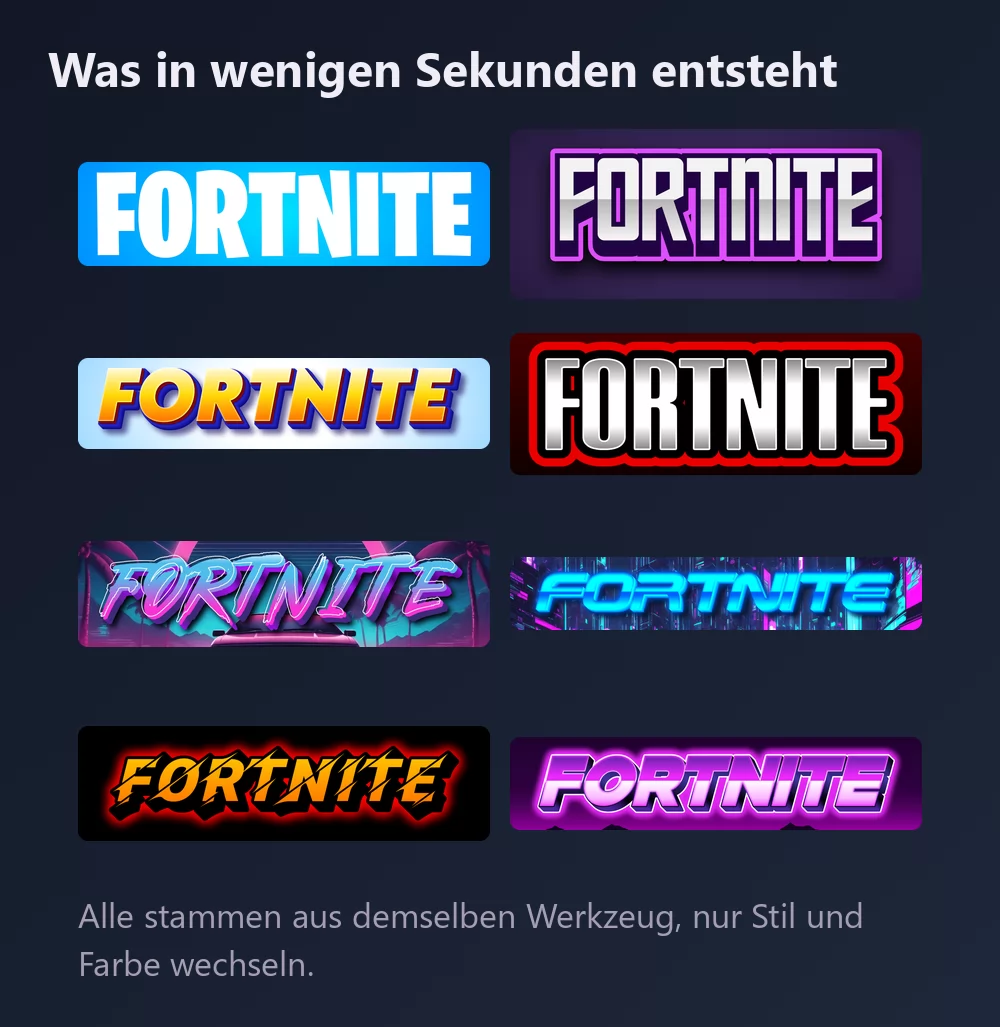
Alle stammen aus demselben Fortnite-Schriftgenerator, nur mit einem anderen Stil aus der Liste. Nichts zu installieren, kein Konto.
Über die Fortnite-Schrift
Fortnite ist ein Sandbox-Survivalspiel von Epic Games und People Can Fly. Es erschien am 25. Juli 2017 im kostenpflichtigen Early Access, und erst der später hinzugekommene kostenlose Battle-Royale-Modus machte daraus ein Phänomen.
Die Schrift im Logo ist Burbank Big Condensed von Tal Leming, in abgewandelter Form verwendet. Burbank ist eine Displayfamilie, gebaut für genau solche Aufgaben, und umfasst rund zwanzig Schnitte. Burbank Big gibt es in drei Breiten mit je vier Gewichten, und die Begleiterin Burbank Small ist für kleine Größen gezeichnet, in vier Breiten mit je einer Kursiven.
Fortnite-Text erstellen
Schritt 1. Das Wort eintippen
Öffne den Generator und ersetze den Beispieltext durch deinen eigenen: einen Namen, ein Squad-Kürzel, einen Kanalnamen, einen Videotitel. Die Buchstaben werden beim Tippen neu gezeichnet.
Schritt 2. Einen Stil wählen
Der Klassiker sind fette weiße schmale Versalien auf einem blauen Verlauf. Im Reiter Stile lassen sich Füllung, Kontur und Schatten getrennt ändern: Die Buchstabenformen bleiben, die Farben wandern woandershin.
Schritt 3. Das Format wählen
Stell das Format vor dem Export ein, dann wird später nichts beschnitten. 16:9 für ein Video-Vorschaubild, ein Quadrat für ein Profilbild oder ein Icon, ein breiter Streifen für eine Kanal-Kopfzeile.
Schritt 4. Herunterladen
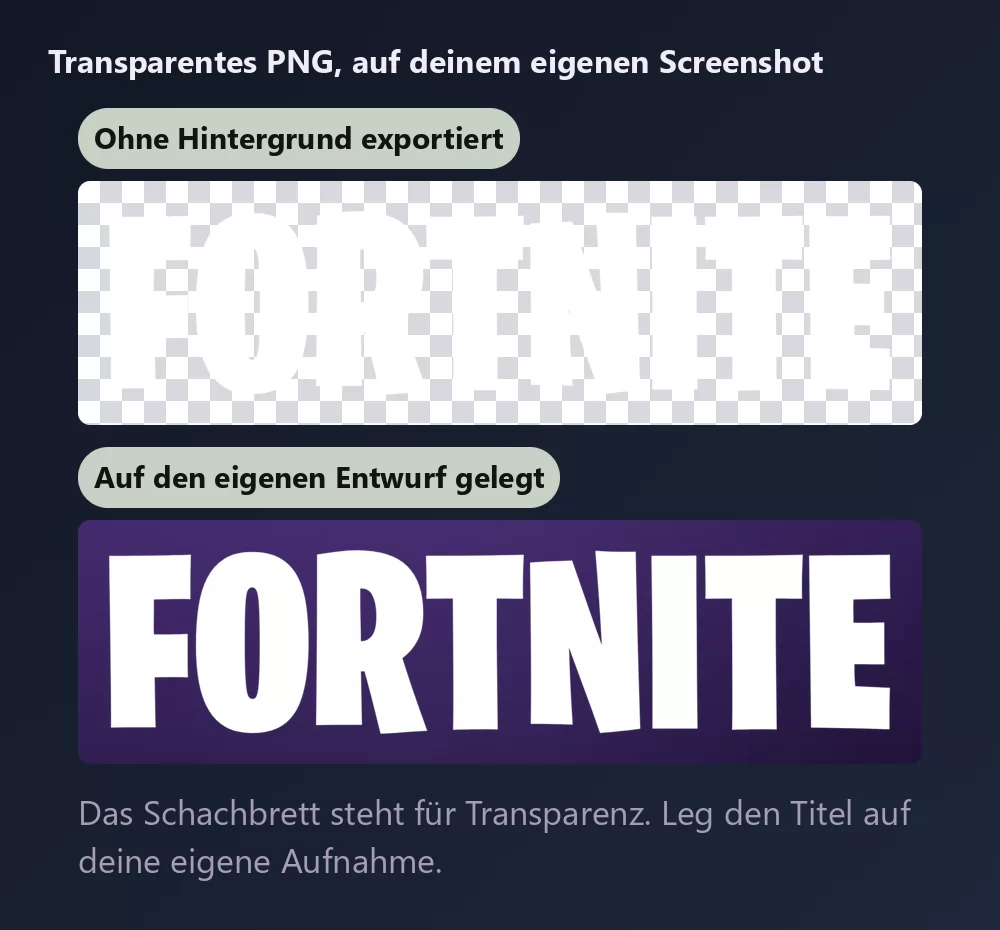
Nimm im Reiter Herunterladen das transparente PNG, wenn der Titel auf deinen eigenen Screenshot soll. Diese Option übersehen die meisten, und für ein Vorschaubild ist sie die entscheidende: deine Aufnahme dahinter, der Titel darüber, kein weißer Kasten drumherum.
Lange Namen füllen die Breite schnell
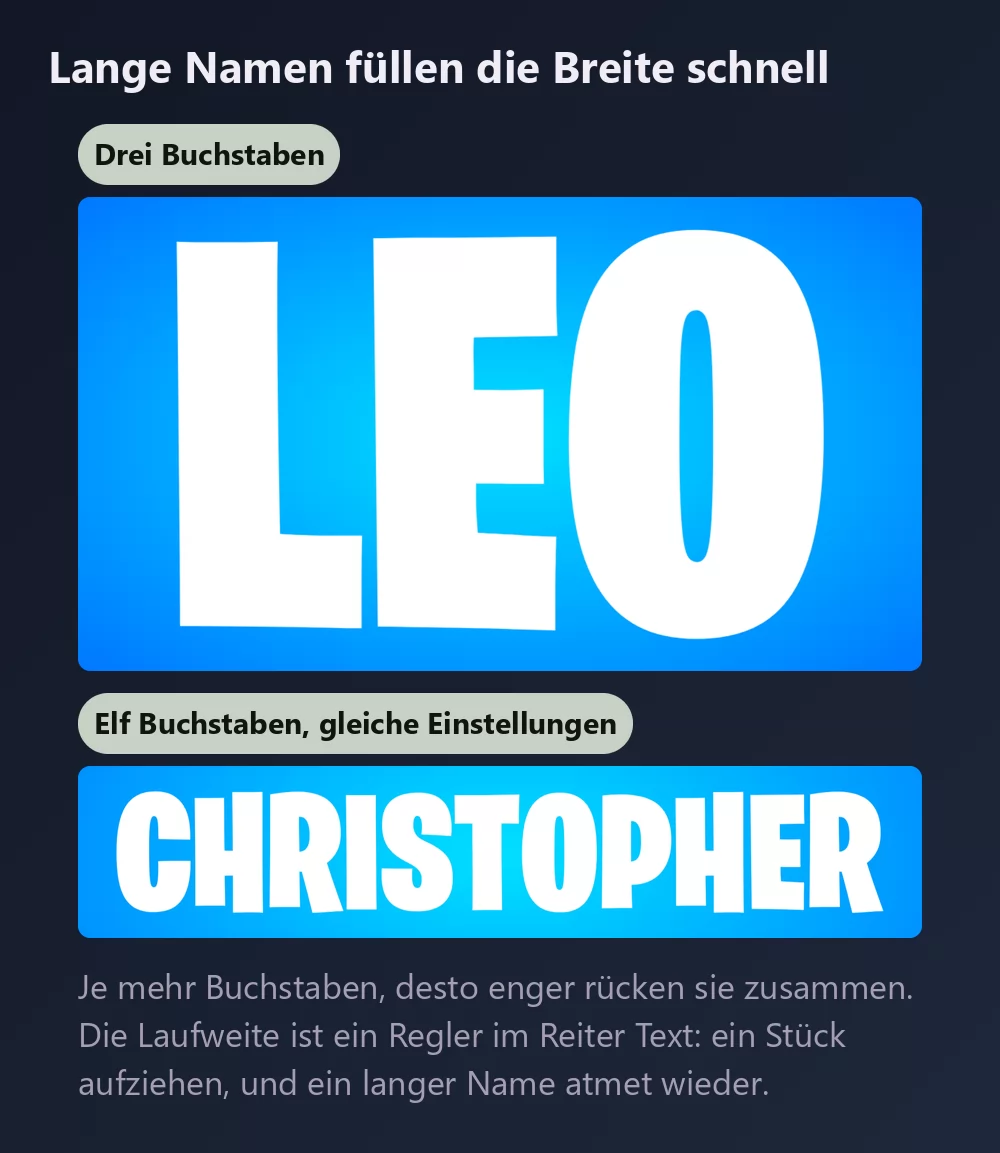
Je mehr Buchstaben, desto enger rücken sie zusammen. Die Laufweite ist ein Regler im Reiter Text: ein Stück aufziehen, und ein langer Name wirkt nicht mehr gequetscht. Im selben Reiter stecken Zoom, Zeilenabstand, Wölbung und Drehung.
Der Logo-Look oder der Esports-Look
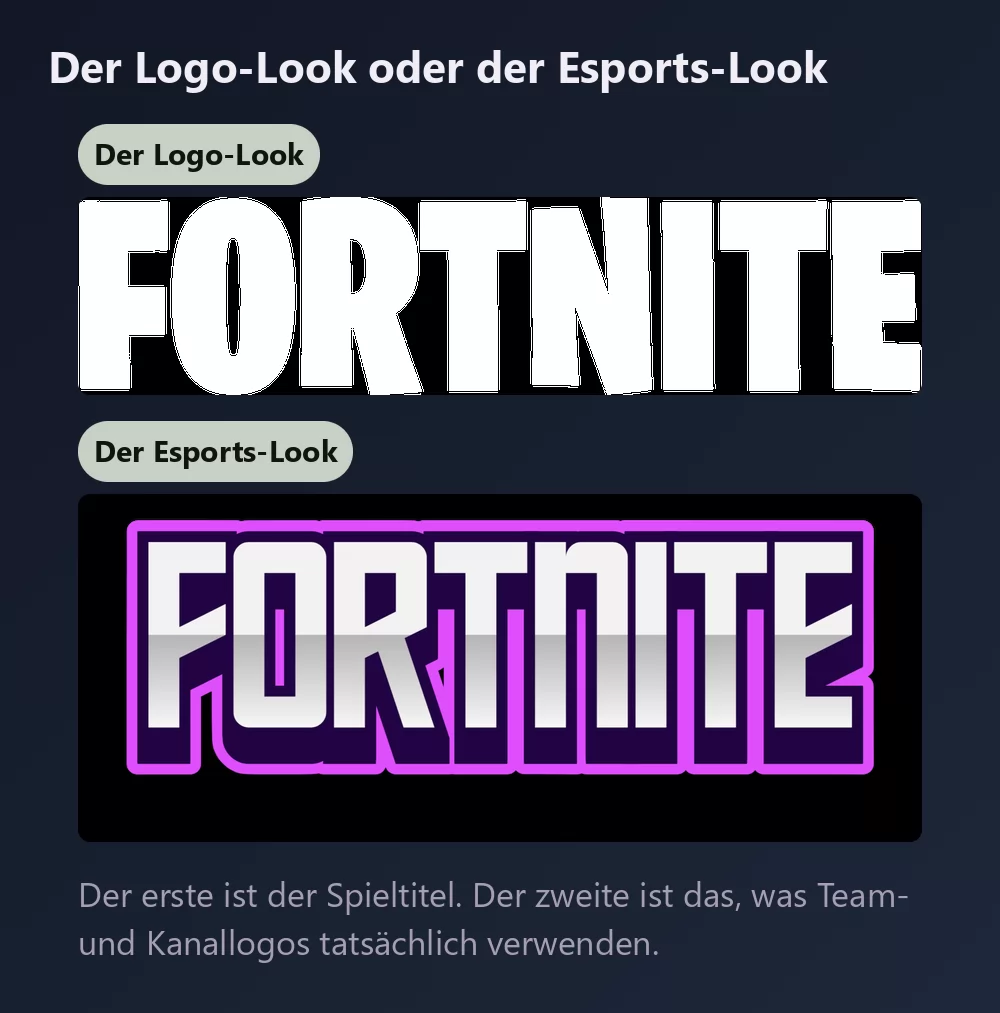
Der Logo-Look ist der Spieltitel selbst: fette schmale Versalien, weiß, um ein, zwei Grad geneigt.
Der Esports-Look behält dieselbe Fette und ergänzt eine farbige Kontur und ein Leuchten. Das nutzen Teamlogos, Kanalbanner und Turniergrafiken tatsächlich, und es hält der Verkleinerung auf Avatargröße weit besser stand als eine schlichte weiße Wortmarke.
Welche Schrift, wenn du eine installieren willst
Keine davon ist ein Klon. Sie geben dieselbe Silhouette, und die ist fast alles, was das Auge in Vorschaubildgröße liest.
Fortnite-Text in Canva erstellen
Canva führt Burbank nicht, aber es führt Anton, du kommst also nah heran, ohne Canva zu verlassen. Für Kontur, Leuchten und Neigung erstellst du den Schriftzug als transparentes PNG und lädst ihn hoch: Er landet direkt im Design und bleibt scharf.
Fortnite-Text in Photoshop erstellen
Installiere Anton oder Bebas Neue, tippe deinen Text in Versalien und baue die Behandlung mit Ebenenstilen:
- Verlaufsüberlagerung, von einem hellen zu einem tieferen Blau, von oben nach unten.
- Kontur, auf Außen, in Weiß oder einer kräftigen Farbe, dick.
- Schein nach außen in derselben Farbe wie die Kontur, geringe Deckkraft, weit.
- Schlagschatten, eng und dunkel.
Dann drehe die ganze Textebene um ein bis zwei Grad. Dieser letzte Griff ist winzig und macht den Unterschied zwischen einer Wortmarke und einem Spiellogo.
Fortnite-Text in Word erstellen
Installiere die Schrift, tippe deinen Text und nutze die Texteffekte für Kontur und Schatten. Word kann weder ein echtes äußeres Leuchten noch eine Verlaufsfüllung präzise, das Ergebnis bleibt also flach. Für ein Vorschaubild oder alles Veröffentlichte sieht ein exportiertes PNG besser aus.
Wie bekomme ich einen transparenten Hintergrund? Wähle im Reiter Herunterladen das transparente PNG und leg den Titel auf deinen eigenen Screenshot.
Warum wirkt mein Text neben dem echten Logo flach? Meist liegt es an Kontur, Leuchten und der leichten Neigung, nicht an der Schrift. Diese drei leisten mehr als die Buchstabenformen.